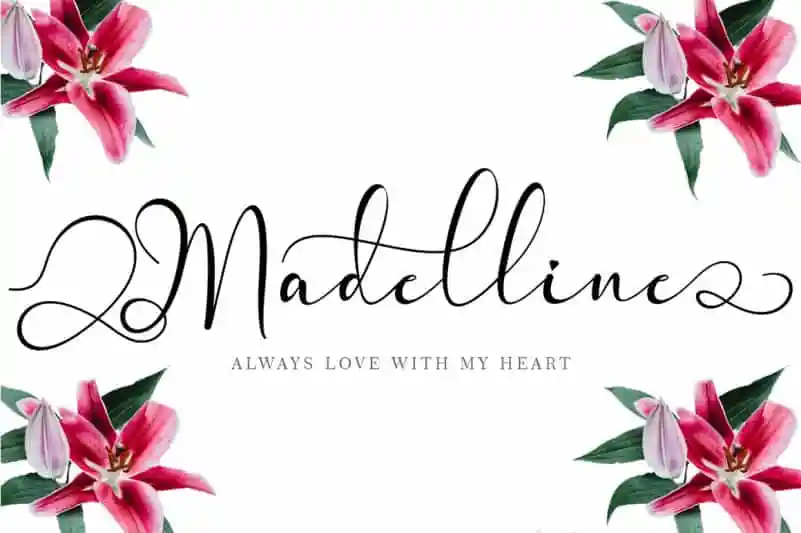
Madelline Calligraphy Font – Download Grátis
Este belíssimo ‘Madelline Calligraphy Font’ se destaca entre as demais tipografias com seu estilo elegante e romântico. Inspirado na elegância do nome de origem Madeline, esta font é ideal para uma variedade de aplicativos, desde criação de cartas, selos e logotipos até a formatação de status no Facebook ou Instagram. Ideal para quem busca um toque único em sua identidade visual, este font é perfeito para wedding designs, personalização de marcas, cartões de convite e assinaturas, bem como promoções de negócios e publicação de mensagens pessoais. Com alto nível de qualidade, o ‘Madelline Calligraphy Font’ oferece um desempenho excepcional em sua aplicação, tornando-se uma opção confiável para quem deseja dar um toque de requinte à suas criações digitais.